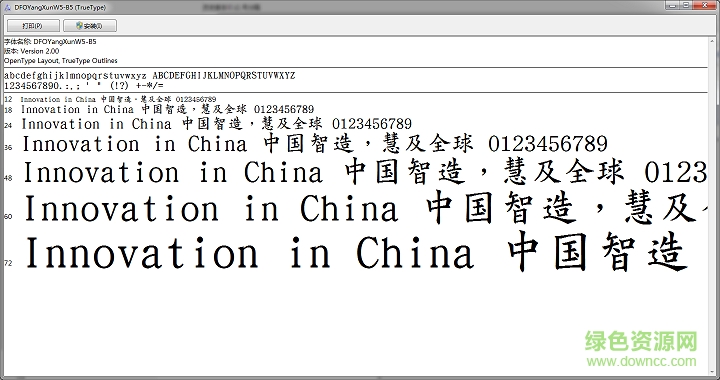
華康歐陽(yáng)詢(xún)體w5是由歐陽(yáng)詢(xún)創(chuàng)作的中文簡(jiǎn)體字。該字體線(xiàn)條優(yōu)美,字形端莊,極具美觀。喜歡的朋友,喜歡這款字體的用戶(hù)趕快來(lái)綠色資源網(wǎng)下載體驗(yàn)吧!
華康歐陽(yáng)詢(xún)體w5字體端正大方得體,整體效果非常出色,并且字庫(kù)完整,可以適用于名片設(shè)計(jì)、平面設(shè)計(jì)、廣告設(shè)計(jì)、報(bào)紙雜志、企業(yè)LOGO、商標(biāo)注冊(cè)、電視臺(tái)廣告等領(lǐng)域!